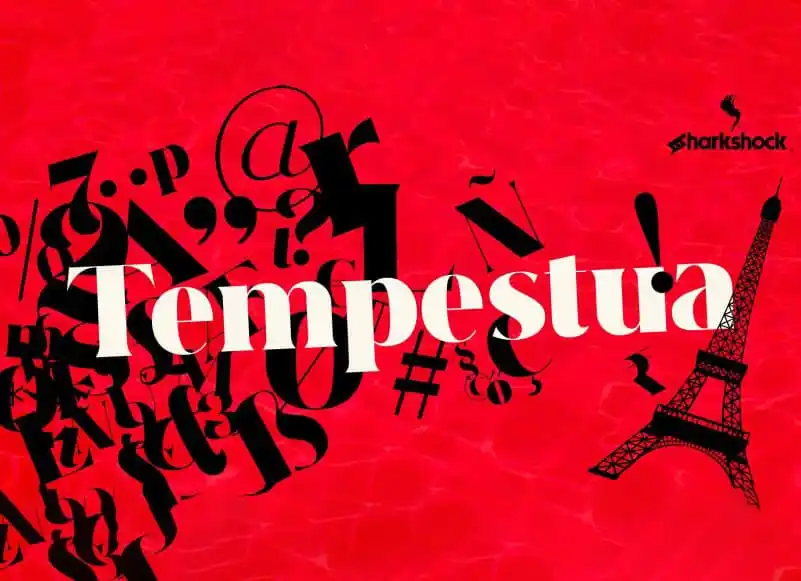
A Tempestua Serif Font é uma tipografia serif que traz modernidade com suas linhas afiladas e riscos agressivos. Esta tipografia se destaca pela contraste entre linhas finas, como as que cobrem os espaços entre as letras, e linhas mais grossas, criando um contrastão notável. As letras minúsculas da Tempestua apresentam seus serifs removidos e tops arredondados para uma aparência elegante e distinta. Suas curvas sutis garantem que os olhos se movam por toda a página, garantindo que as pessoas não fiquem indiferentes à sua beleza. Use a Tempestua para logos luxuosos de marcas, revistas ou até mesmo o título de uma grande produção cinematográfica. O pacote completo da fonte inclui suporte básico em latim e latim extendido com diacriticos, bem como suporte para polonês e kerning.